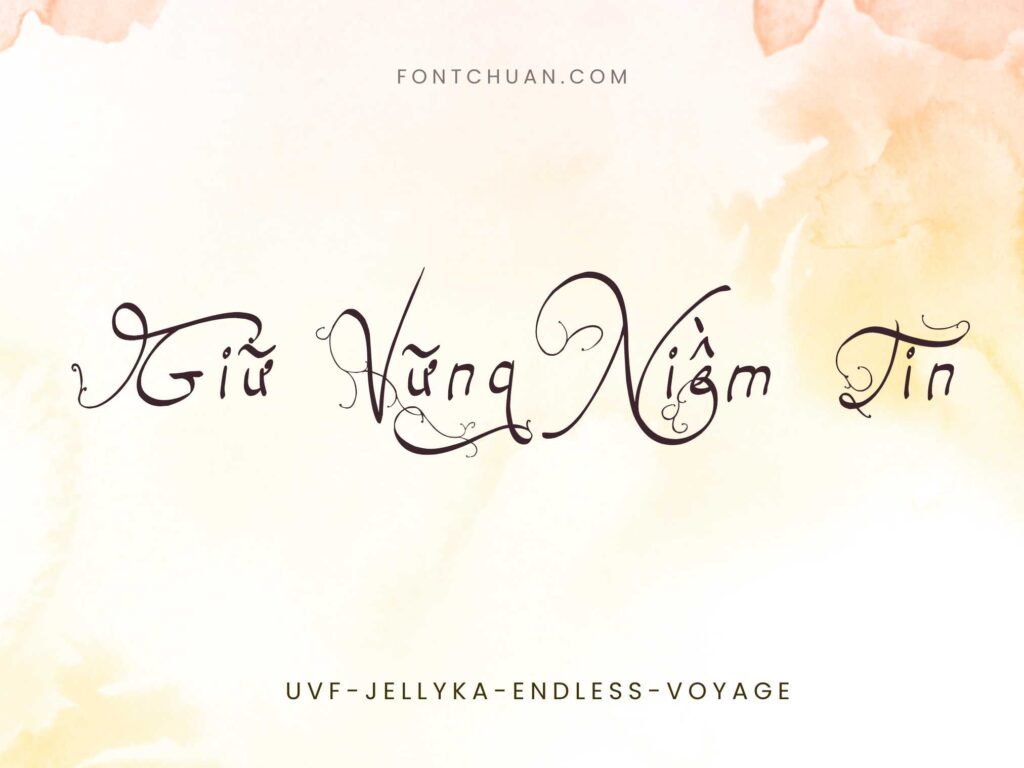
Font UVF Jellyka Endless Voyage Việt Hóa
Jellyka Endless Voyage là một kiểu chữ mang phong cách viết tay nghệ thuật với các đường nét uyển chuyển và tinh tế. Font này mang đến vẻ đẹp cổ điển nhưng đầy sáng tạo, giúp tạo dấu ấn đặc biệt trong thiết kế. Với độ cong mềm mại và kiểu chữ tự nhiên, Jellyka Endless Voyage là lựa chọn lý tưởng cho các thiết kế cần sự trang nhã và nghệ thuật.
Font này phù hợp với nhiều ứng dụng như thiệp cưới, trang trí sự kiện, tiêu đề sáng tạo, bìa sách và các thiết kế đồ họa khác. Trong ngành công nghiệp sáng tạo, Jellyka Endless Voyage đặc biệt hữu ích trong lĩnh vực thiệp cưới, chụp ảnh cưới, quảng cáo và các sản phẩm thiết kế mang phong cách nghệ thuật.
Bên cạnh các ứng dụng trang nhã và nghệ thuật, Jellyka Endless Voyage còn là một font valentine lý tưởng để thiết kế các sản phẩm lãng mạn và ngọt ngào, như thiệp Valentine, banner hay poster dịp lễ tình nhân. Với các đường nét uyển chuyển, mềm mại và tự nhiên, font này giúp các thiết kế vừa tinh tế, vừa ấm áp và gần gũi, mang đến cảm giác lãng mạn phù hợp cho các dự án sáng tạo về tình yêu và các dịp đặc biệt.